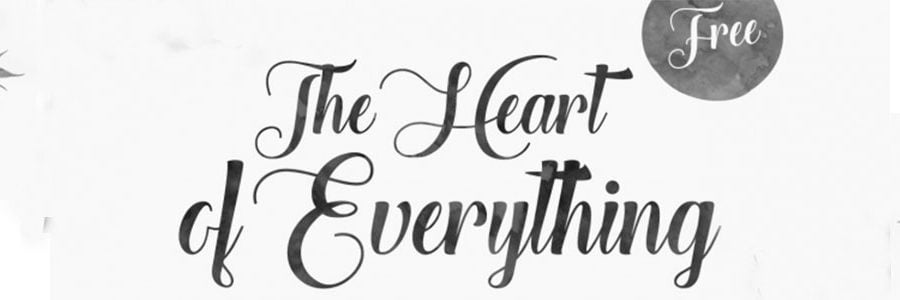
The heart of everything: Typographie gratuite
The heart of everything (Le “coeur de tout”) est une police de caractères de type manuscrite gratuite créée par, Mats-Peter Forss, graphiste et Misti Hammers designer de police.
Les images de prévisualisation ont été créées pour ce type de police fantastique de Misti’s Fonts. Il s’agit d’une police de caractères courbée, manuscrite et parfaitement flottante avec une teinte de cette sensation luxueuse des années 30.
Cette typographie est parfaite pour vos créas sur des affiches aux grands formats, des brochures, les logos et la décoration graphique mais aussi pour les cartes de visite originales.